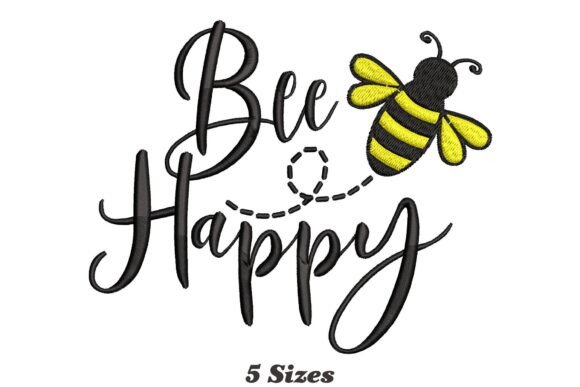
Bee Happy
์˜ฌ๋ฐ”๋ฅธ ๋””์ž์ธ ์š”์†Œ๋ฅผ ์ฐพ๋Š” ๊ฒƒ์€ ์–ด๋ ค์šธ ์ˆ˜ ์žˆ์ง€๋งŒ Bee Happy๋Š” ์ž‘์—…์„ ์ฆ‰์‹œ ํ–ฅ์ƒ์‹œํ‚ค๋Š” ๋›ฐ์–ด๋‚œ ์ปฌ๋ ‰์…˜์„ ์ œ๊ณตํ•ฉ๋‹ˆ๋‹ค.
์ •๋ฐ€ํ•˜๊ฒŒ ์ œ์ž‘๋œ Bee Happy๋Š” ๊น”๋”ํ•œ ๋ฒกํ„ฐ, ๋ถ€๋“œ๋Ÿฌ์šด ํƒ€์ดํฌ๊ทธ๋ž˜ํ”ผ ๋ฐ ์•ˆ์‹ฌํ•  ์ˆ˜ ์žˆ๋Š” ์ƒ์—…์šฉ ๋ผ์ด์„ ์Šค๋ฅผ ์ œ๊ณตํ•ฉ๋‹ˆ๋‹ค.
์ƒํ’ˆ์— ์ „๋ฌธ์ ์ธ ๊ฐ๊ฐ์„ ๋”ํ•˜๊ณ ์ž ํ•˜๋Š” ๊ณต์˜ˆ๊ฐ€, ๊ทธ๋ž˜ํ”ฝ ๋””์ž์ด๋„ˆ ๋ฐ ์†Œ๊ธฐ์—… ์†Œ์œ ์ž์—๊ฒŒ ์ ํ•ฉํ•ฉ๋‹ˆ๋‹ค.